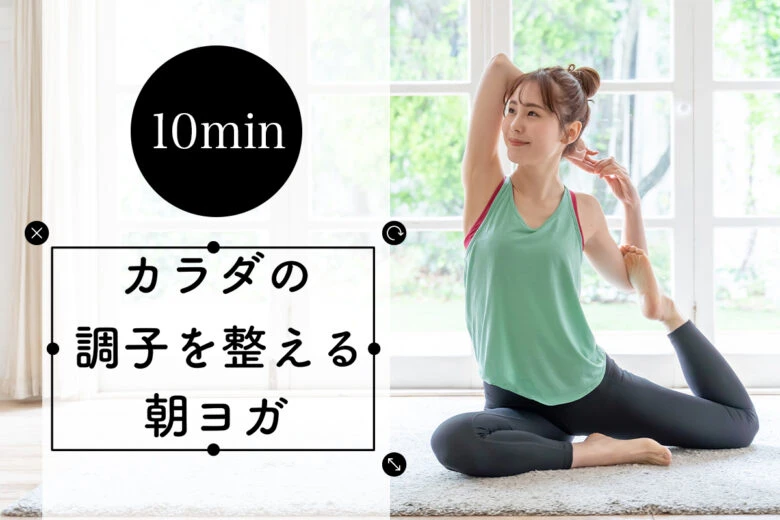
独特の情感を持つ日本語のフォントは、世界でも人気です。ひらがな、カタカナ、漢字の3種類から成る日本語フォントは、英語フォントとは異なるユニークさを持っています。
一昔前は、明朝体やゴシック体などフォントの種類は限られていましたが、現在では日本語のフォントのバリエーションも増え、 文字としてだけではなく、デザインとしての価値をも見出しています。
日本語のフリーフォントでつくるデザイン
フォントは単なる文字ではありません。それぞれに異なる雰囲気やビジュアルイメージがあるため、フォントだけで文字デザインをつくることも可能です。以下では、文字デザインを作るためのポイントをご紹介!
フォントの組み合わせ
ここでは、各フォントの効果的な組み合わせ方について解説します。
日本語と英語のフォントをミックスさせる
文字の性質が異なる日本語と英語。しかし、系統が近いフォントを探すことで統一感が生まれやすくなります。また、太さやサイズが近いものを選べば、一体感を生み出すことも。
同系統のフォントとしては、
・日本語フォントのゴシック体 & 英語フォントのサンセリフ体
・日本語フォントの明朝体 & 英語フォントのセリフ体
などがあげられます。
同類のフォントを使う
一つのフォントには、太さ、細さ、傾きなどのバリエーションや、それらをまとめた「フォントファミリー」というグループがあります。フォントファミリーを使うと、バランスを整えられるだけではなく、組み合わせによってアクセントなどもつけられます。
フォントの縦サイズを合わせる
同じくらいの大きさや高さのフォントは、異なるフォントでもうまく組み合わせることができ、バランスの取れた文字デザインに仕上げられます。文字の大きさが揃いつつも、フォント自体は異なるため、個性やユニークな雰囲気を生み出すことも可能です。
コントラストをつける
太さ、サイズ、スタイルなど対照的なフォントを組み合わせることで、コントラストをつくることができます。色々と組み合わせてみることで、思わぬ良い相性を発見することもあるため、サイズや色の濃度を変えて自分好みに調整してみましょう。
フォント選びの注意点
フォントを選ぶときには、いくつかポイントがあります。フォント選びの注意点は、以下の4点です。
簡潔さ
オリジナリティを追求するあまり、つい忘れてしまいがちなのがシンプルさです。複数のフォントを組み合わせると、ごちゃごちゃしてしまい、デザインの効果を弱めてしまうこともあります。そのため、できるだけシンプルさを意識し、心がけるとよいでしょう。
定番フォントは使わない
ユニークなデザインにしたいなら、セリフ体やゴシックなど、文字として読みやすい定番フォントはあえて避けるのもアリです。筆で書いたような行書や手書き風フォントなど、和風のデジタル文字も多いため、ぜひ色々なフォントを試してみてください。
フォントの著作権を確認する
用途によって文字間を調整する
フォントの文字間を微調整するだけで、文字デザインのバランスが一段とよくなることがあります。フォントの縦横の幅を変えると、フォントの個性を変えてしまうため、あまりオススメしませんが、文字間や大きさの調整であれば、フォントの美しさをとどめつつ、優れたフォルムの文字デザインを作成できます。
日本語フォント変わり種
太文字なら強調、筆記体は繊細など、見た人に印象を伝えるフォントには、さまざまな個性があります。ここでは、人気の日本語フォントをご紹介!
アメコミ
カラフルな色使いが特徴的なアメリカンコミックス。ここで使われている数々のフォントは、ポスターやセールスレターのタイトルなどにピッタリです。吹き出しや効果音などにも絶大な効果をもたらすでしょう。
ネオン
夜の街にきらめくネオン管の看板で使用されるフォント。シャドウや光彩などを合わせて使うと、フォントがより一層引き立ち、 近未来感やおしゃれな感が増します。
黒板文字
カフェで黒板にメニューが書かれているのを見たことがありませんか? これはまさに、黒板にチョークで書いたようなフォントです。手書きフォントもここに分類されます。
手書き風フォント
ちなみに、手書きフォントを見つけたい場合は、紙にためしがきして、それに近いフォントを探すことをおすすめします。
ひび割れ
文字に亀裂が走り、割れているようなフォントです。インパクトを与えやすく目を引くため、ロゴに採用されることも多々あります。ニュースペーパーやチラシの見出しにも最適です。
ブラシ
ブラシやペンで書かれたような手書き感があるフォント。筆で書いた時に出るかすれも表現され、デジタル文字なのに、とてもナチュラルな雰囲気を与えます。
四角いフォント
四角いフォントは、丸みのあるフォントとは対照的に文字の四角さが強調されています。日本語はもともと丸みを帯びているため、丸みをゼロするのは難しいのですが、こちらは正方形や長方形などの枠に沿うようなイメージでつくられています。そのため、柔らかさの中に強さを感じさせることも可能。ユニークな見た目で、メッセージ性も高まります。
ドットフォント
ドット(水玉模様)で構成されたドットフォントも、じわじわと人気上昇中です。
Picsartの日本語フォント
ちなみに、日本語フォントは23種類もあるため、フォント選びに困ることはありません(フリーフォントは現在4種類)。ここでは、オススメの日本語フォントをフリーフォントと有料フォント2つずつご紹介!
しねきゃぷしょん(無料)
文字通り、映画の日本語字幕のようなフリーフォントです。日本語だけでなく英字にも対応。レトロな雰囲気でオシャレなフォントですが、少し縦長の文字で読みやすいため、文字として読ませるフォントとしても便利です。YouTube動画のテロップとしても活用できます。
マキナス(無料)
直線的なデザインが特徴のフォントは、無機質でシンプルな印象が好評です。もちろん、ひらがなや漢字もあり、文字デザインとして作成する場合も、独特の個性を表現できます。線画などと組み合わせると、デザインの中に自然と溶け込みます。
アンティーク明朝(有料)
上品な明朝体にレトロ感を加えて、モダンアンティークにしたフォント。文字を読ませるタイプのフォントとして明朝体は重宝されていますが、アンティーク明朝体は読ませつつも、ロゴデザインなどにもマッチしています。
A丸ゴシック
丸っとした可愛らしさの中に、シュッとした大人らしさを感じさせるフォントです。文字の線と線で作られている内側の空間の丸みが、通常の丸ゴシックより少し抑えられているため、明朝体のような和や伝統的なテイストを感じさせられます。どのような媒体にもマッチする万能なフォントです。